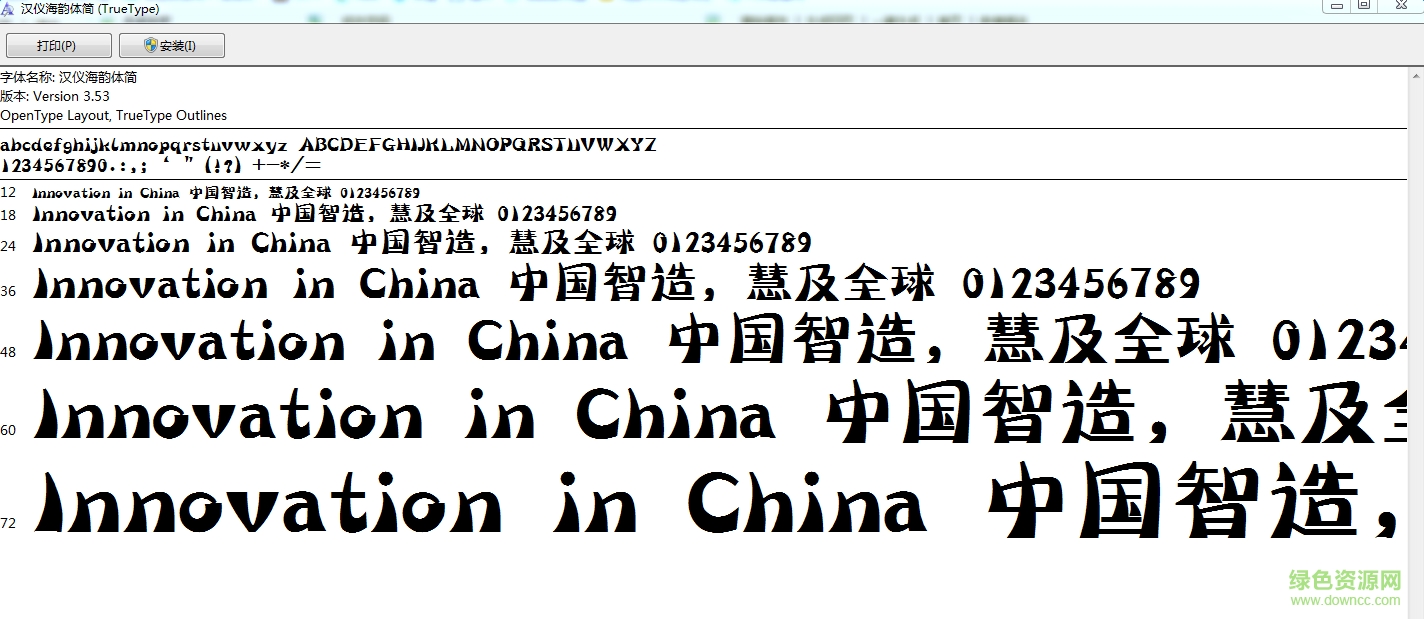
hyk3gj字體又稱漢儀海韻體簡,是漢儀制作的一款字型優(yōu)美的電腦字體,該字體給人非常古典優(yōu)雅的感覺,適用于二次元?jiǎng)?chuàng)作,感興趣的朋友歡迎來綠色資源網(wǎng)下載使用!
hyk3gj字體是一款藝術(shù)字體,字體整體豐富多彩,有一種卡通的風(fēng)格味道,整體效果十分出色,可以用于廣告設(shè)計(jì)、平面設(shè)計(jì)、印刷包裝、藝術(shù)設(shè)計(jì)、網(wǎng)站設(shè)計(jì)領(lǐng)域。